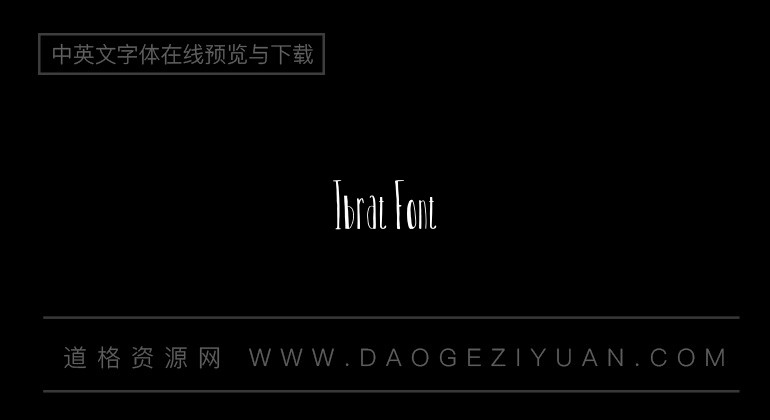
Ibrat Font是一种Unicode字体,它是为使用Uzbekistan的拉丁文语言而设计的。该字体由Ibrohim Hamidov开发。 Ibrat Font具有优秀的可读性和字母形状,可用于印刷和屏幕上的文本。它包含Uzbekistan语言所需的所有字符和标点符号。 此外,Ibrat Font是一种免费字体,可在多种操作系统和应用程序中使用,例如Windows、Linux、Mac OS和Adobe应用程序等。内容介绍
Ibrat Font是一款非常不错的手写艺术字体,具有很好的视觉感,适合于文化类的宣传设计、商业类品牌的广告和产品包装设计以及个性化文字排版等较多场景。